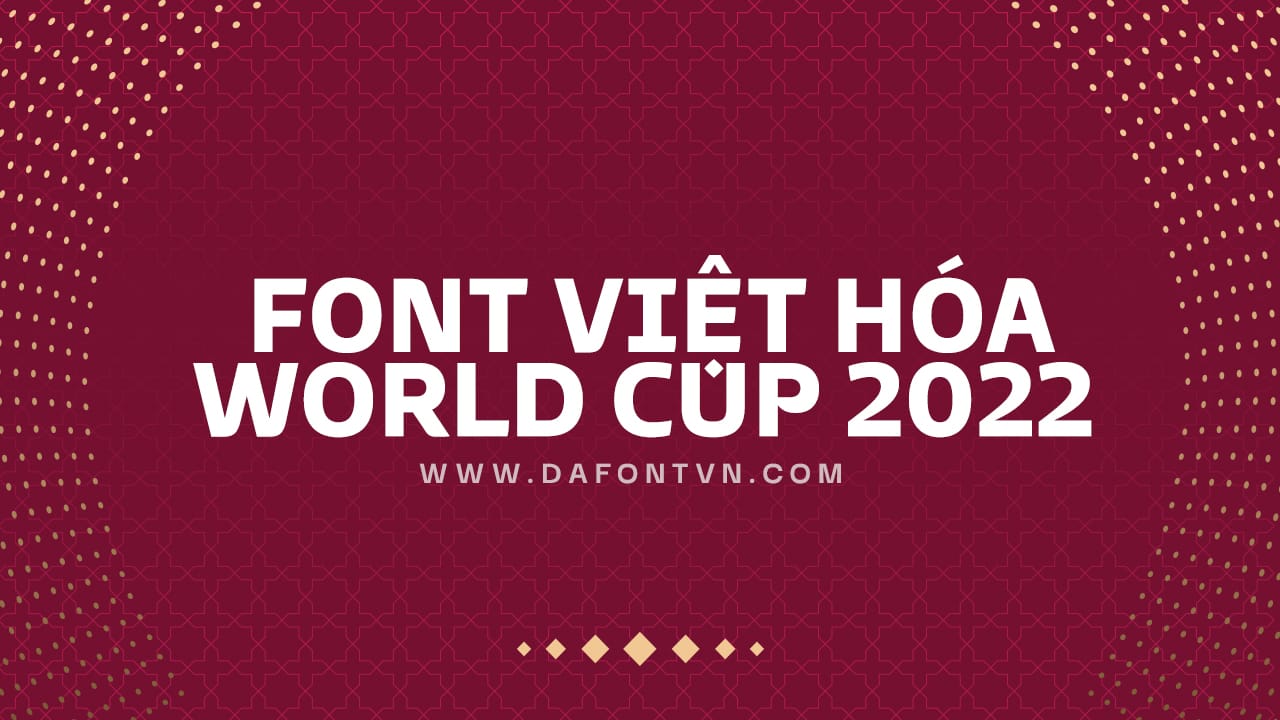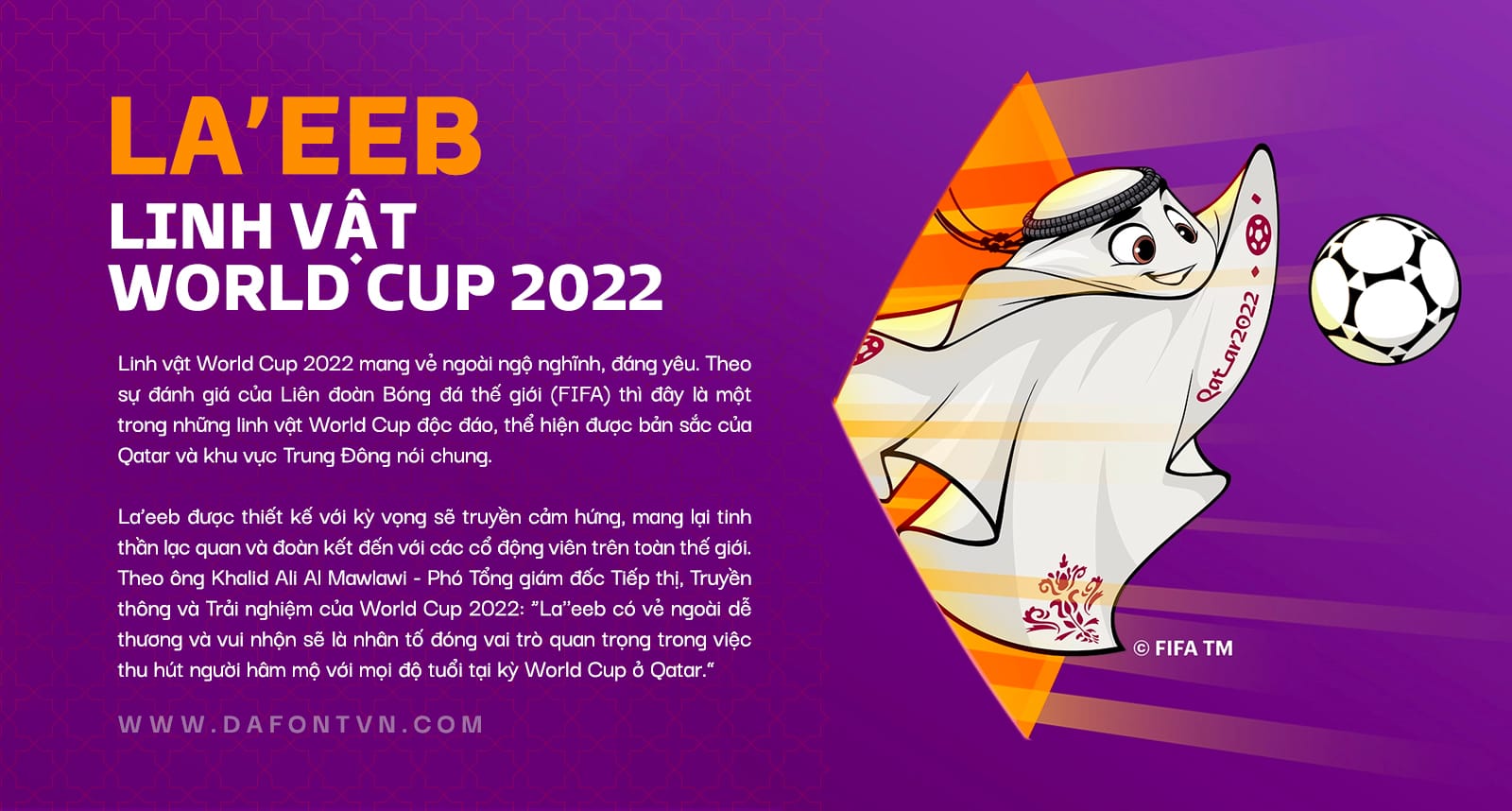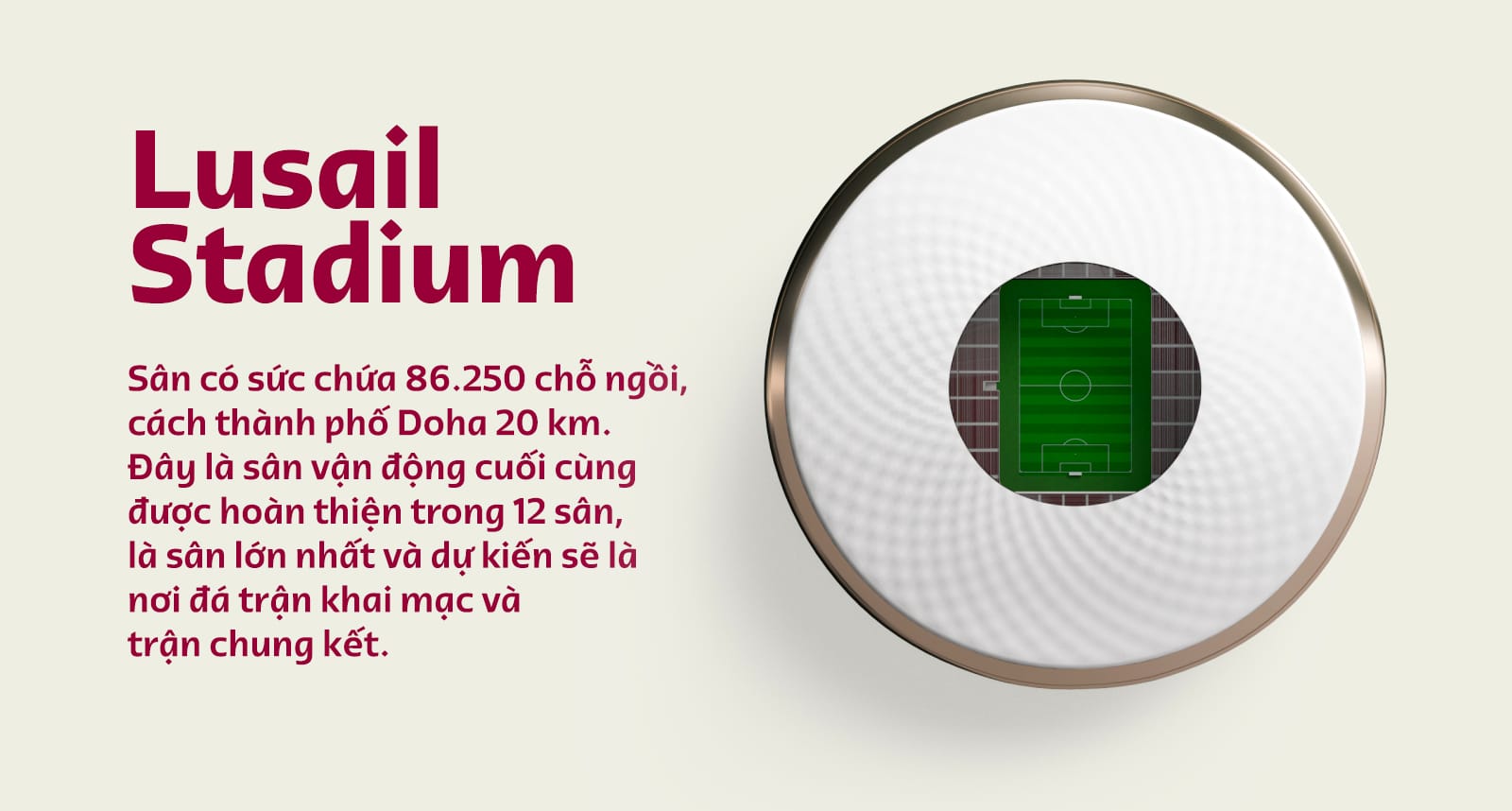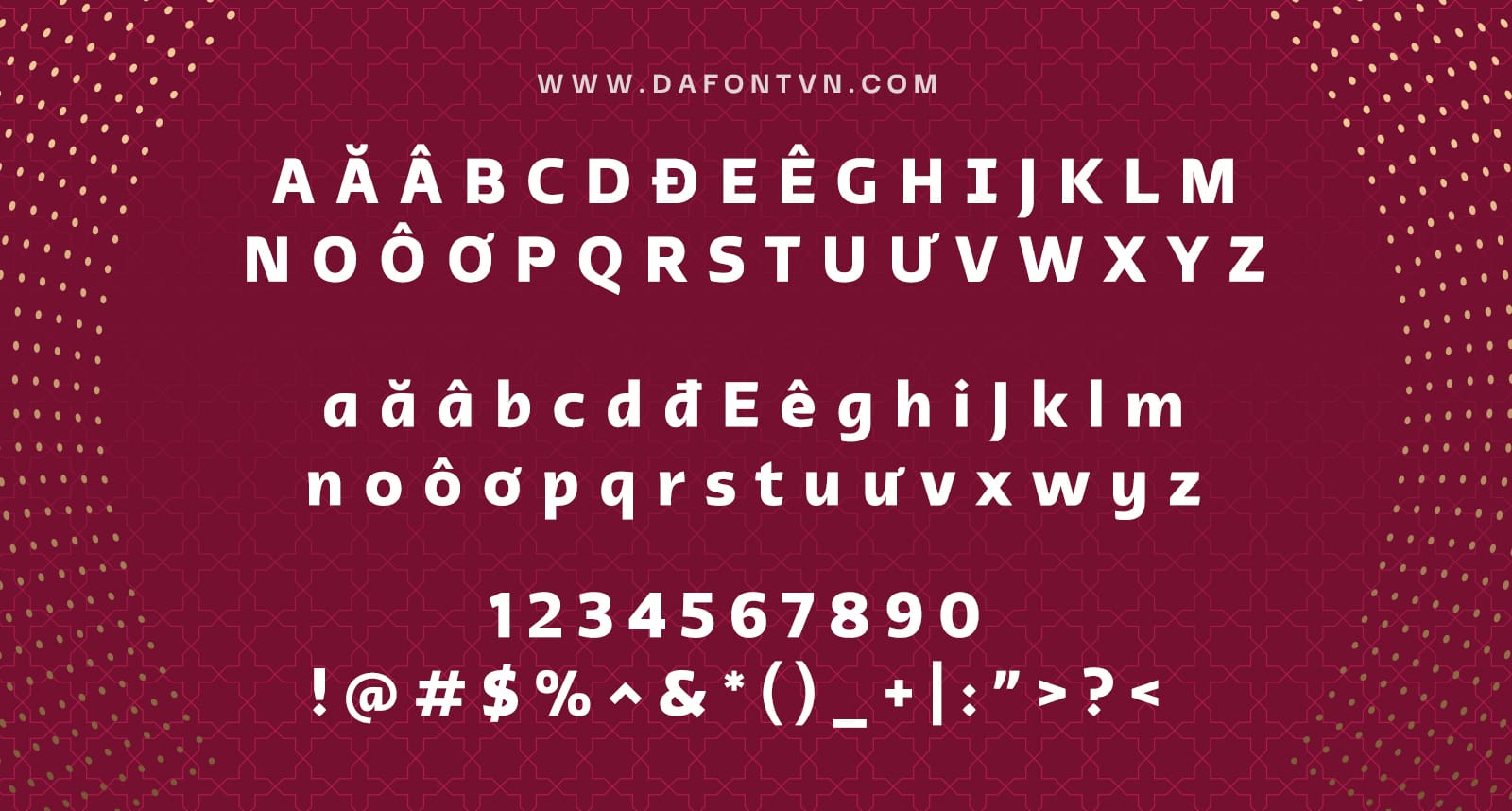
Font World Cup 2022 Việt hóa (3 font)
World Cup giải thi đấu bóng đá lớn nhất hành tinh, mỗi quốc gia đăng cai đều có bộ nhận thương hiệu riêng trong đó
Font World Cup 2022 tại Qatar cũng được thiết kế riêng, bộ font này được sử dụng trong tất cả các sản phẩm thương mại, các ẩn phẩm, website, poster, banner, quảng cáo, áo, túi…
Bộ font World Cup 2022 Việt hóa được thiết kế khá ấn tượng các đường nét mềm mại giống như biểu tượng của FIFA World Cup và nước chủ nhà Qatar. Font bao gồm 3 kiểu Medium, Bold, Heavy, với các nét chữ được thiết kế đậm vì vậy font chữ này phù hợp cho tiêu đề với văn bản kích thước lớn.